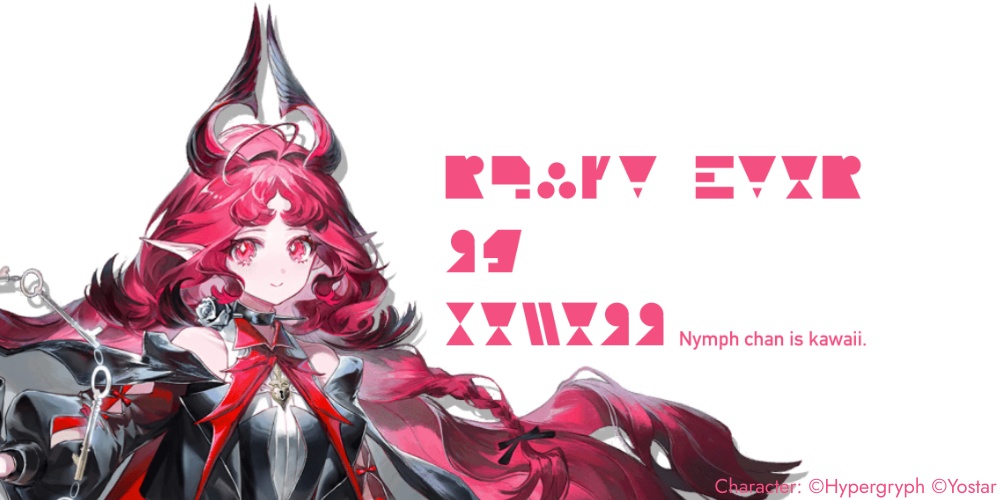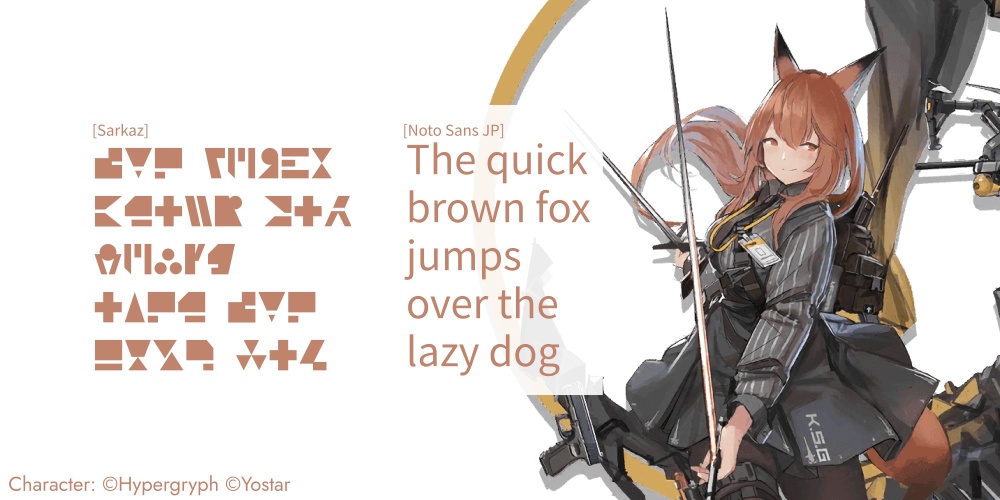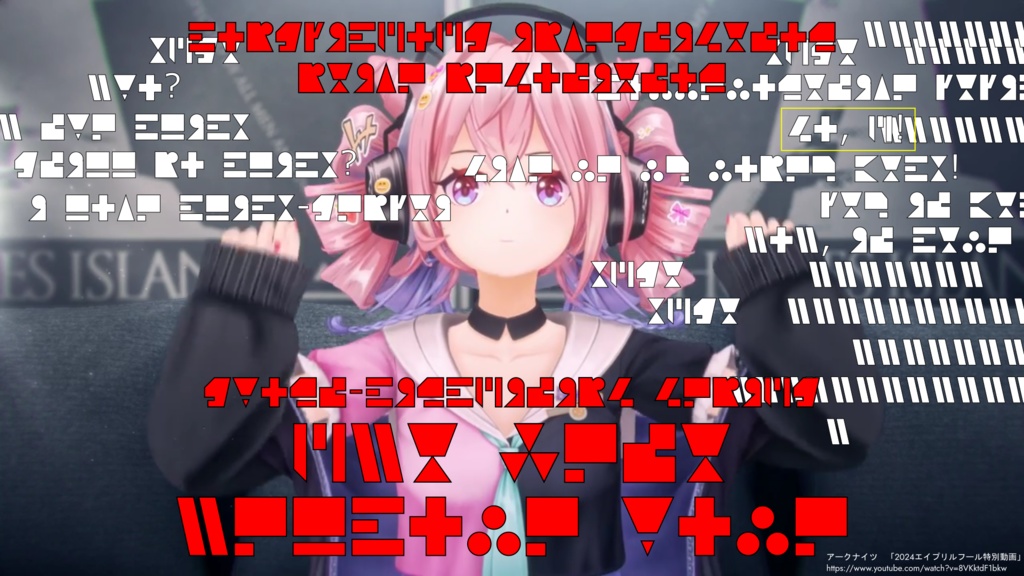
サルカズフォント
- サルカズ語に対応した『Arknights』攻略動画を作りたい。 - 『サルカズ戦争史』を出版したい。 - 気になるジャールのあの子に恋文を認めたい。 そんなあなたに!誰でも使えるサルカズフォントが出来ました! ――始めに - 「サルカズフォント」はゲーム『Arknights』に登場するサルカズ文字を再現した書体です。 - 「サルカズフォント」はゲーム『Arknights』の二次創作を目的に制作されました。 ――仕様 - 収録文字: 英字アルファベット[A~Z,a~z]、アラビア数字[0~9] - 約物(句読点や括弧など)は現在未対応です。 - アルファベットの大文字と小文字は見た目が同じです。 ――利用可能範囲 ※『Arknights』では、二次創作・ゲーム実況配信及び動画投稿に関するガイドラインを設けています(https://www.arknights.jp/fankit/guidelines)。 同梱のフォントファイル自体も『Arknights』を基にした二次創作物に当たります。 このフォントファイルを利用して何らかの創作/制作を行う場合、当ガイドラインに必ず目を通し、それに従ってください。 -許可していること 1. 非営利目的での個人利用 2. 『Arknights』の同人活動での利用(同人誌、動画、ゲームなど) 3. 当フォントファイルの改造/改変 4. 当フォントファイルの改変物の配布 (改変物の配布に関する規約は、同梱したReadMeより「使用許諾と著作権について」を参照) -禁止していること 1. 当フォントファイル及びその成果物の商用利用 2. 当フォントファイルの再配布(ゲームなど電子データで利用する際は、当フォントファイルを再配布しない形にしてください)